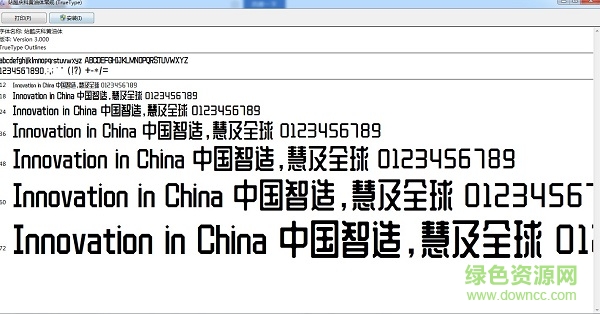
站酷慶科黃油體是一款可以用在平面設(shè)計、影視海報等領(lǐng)域的特色字體,線條圓潤流暢,字形精致,非常具有設(shè)計感,識別度也十分高,喜歡的朋友快來下載吧!
1.筆劃的每一個直角,都被處理成了半徑為4pt的圓角。
2.在設(shè)計中需遵循筆劃簡化但不省略,筆劃角度盡量為垂直角度。
3.字體部首的右下角均為45°缺角,提高了字體視覺中心。
4.有效的解決了一些字體因筆劃交叉,字體閱讀困難的毛病。